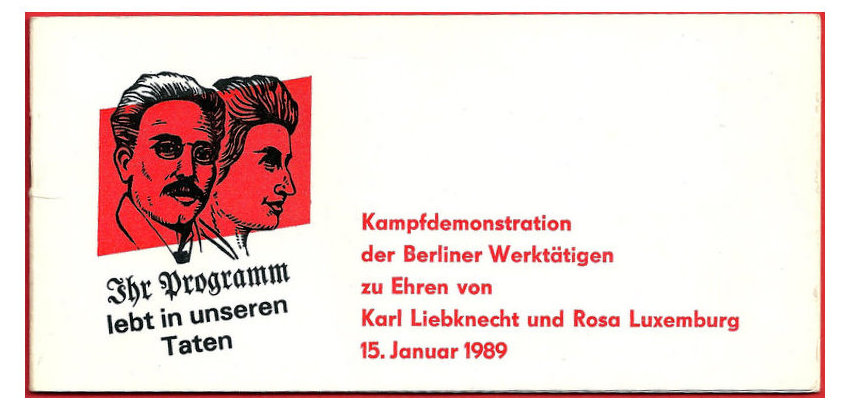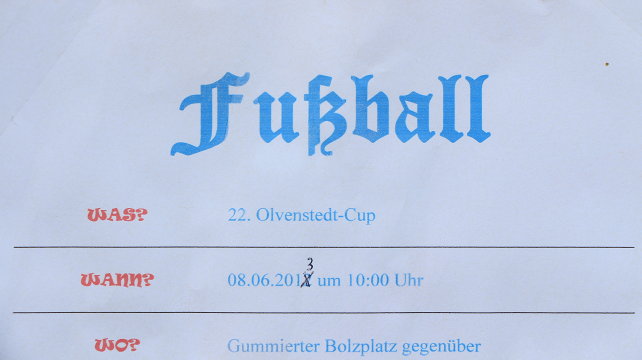
image-628738-galleryV9-lkcf.jpg Eine der spätesten staatsoffiziellen Verwendungen von Fraktur überhaupt? Interessant erscheint mir besonders, dass die Fraktur hier in einem aus offizieller DDR-Sicht positiven und zukunftsgerichteten Kontext verwendet wird, statt z.B. für angeblich überkommene bürgerlich-kapitalistische Ideen zu stehen.
Soweit ich mich an die wenigen Frakturanwendungen in der DDR erinnere, wurde diese eher im Sinne von »historisch; alt; abgeschlossene Periode« verwendet als im Sinne von »reaktionär; bürgerlich; faschistisch« — also alles in allem recht emotions- und ideologiefrei. Ich kann mich freilich auch nicht an moderne Adaptionen erinnern, die der Fraktur eine Brücke in die Gegenwartstypographie gebaut hätten. Fraktur war Geschichte — Punkt. Hatte Typoart eigentlich eine Fraktur im Angebot? Ich kann mich nicht erinnern. Sie war aus dem Alltag schon weitgehend verschwunden, aber, wie mir scheint, eher aus Desinteresse und allgemeiner Fortschrittsgläubigkeit heraus. Die offizielle Ästhetik war halt die eines Plattenbaus, das hat sich auch in der Typographie bemerkbar gemacht und da war für Schnörkel kein Platz.
Aber, wie gesagt: Seltsamerweise scheint der Fraktur ausgerechnet in der DDR die Discreditierung als Nazischrift erspart geblieben zu sein.
Hatte Typoart eigentlich eine Fraktur im Angebot?
Typoart hatte an gebrochenen Schriften die Luthersche Fraktur, die Caslon-Gotisch und eine Schwabacher im Sortiment. Als digitalisierte Version sind diese Schriften aus der Typoart-Bibliothek bei Elsner + Flake zu beziehen. (Die Verlinkungen führen dort hin.)
Luthersche Fraktur:
»Volker Küster wählte typische Merkmale aus und vereinigte sie mit viel Stilgefühl zu einer sehr geschlossen wirkenden Werkschrift. Noch schmaler, etwas kräftiger und vor allem mit reicheren Schmuckdetails versehen, präsentieren sich die Großkegelgrade, die der Grafiker Herbert Lemme zeichnete.«
Luthersche-Fraktur.jpg
Caslon-Gotisch:
»Die Fotosatz-Replik wurde von Erhard Kaiser künstlerisch betreut.«
Caslon-Gotisch.jpg
Schwabacher:
»Die künstlerische Überarbeitung durch Herbert Lemme orientierte sich an historischen Drucken. Anstelle der falschen Versalziffern, wie sie von anderen Schwabachertypen bekannt sind, wurden bei der vorliegenden Fotosatzschrift Minuskelziffern eingesetzt.«
Schwabacher.jpg
Kein Widerspruch, verehrter Pachulke. Ich meinte das mit den negativ bürgerlichen Konnotationen nur als Beispiel für etwas, das man vielleicht etwa erwarten können nicht dass es so war. Ich bin mir sicher, dass man zum Lutherjahr 1983 einiges an gebrochenen Schriften gesehen hat. Trotzdem hat mich die Verwendung hier für Liebknechts und Luxemburgs »Programm« einigermaßen überrascht. Denn dieses war nach offizieller Lesart ja alles andere als »historisch; alt; [Teil einer] abgeschlossene[n] Periode«.
Ich meinte das mit den negativ bürgerlichen Konnotationen nur als Beispiel für etwas, das man vielleicht etwa erwarten können – nicht dass es so war.
So in etwa hatte ich Dich auch verstanden.
Die Kombination von Fraktur und Grotesk im Beispiel war einfach das Mittel des Graphikers, die Verbindung der objektiv ja doch historischen Personen Liebknecht / Luxemburg mit der DDR-Gegenwart herzustellen. Und damit war er durchaus »auf Linie«.
Stimmt, so erklärt ist das durchaus plausibel. Ich wäre mir nur nicht sicher gewesen, ob die Bonze, die diese Arbeit abnehmen musste, das auch so logisch gesehen hätte und den armen Gestalter nicht etwa in Generalverdacht genommen hätte, L und L in eine »revanchistische« Ecke zu stellen. Du weißt ja selbst, mit welch Lächerlichkeiten man so anecken konnte.
Ich betrachte dieses Thema übrigens nicht als abgeschlossen. Wenn ihr noch andere Beispiele von Fraktur in der DDR herum zu liegen habt, immer her damit! :huhu:
Ich denke, durch die gut belegte Tradition von Fraktur in der KPD (Thälmann-Wahlplakate u. dgl.) wäre der Graphiker gut abgesichert gewesen. Vermutlich sind das auch die Assoziationen gewesen, die hier sowohl bei Graphiker als auch bei Zensurbehörde die entscheidenden Trigger betätigt haben.
Volker Küster wählte typische Merkmale aus und vereinigte sie mit viel Stilgefühl zu einer sehr geschlossen wirkenden Werkschrift.
Und das ist nicht nur Werbeunsinn sondern stimmt ausnahmsweise mal. Die Luthersche Fraktur ist eine der ausgeglichensten, schönsten Frakturschriften überhaupt. Und die Typoart-Luthersche dürfte die beste digital verfügbare Fraktur sein!
ich finde, bei einer fraktur sollten auch die ziffern gebrochen sein, zumindest so anmuten. und natürlich minuskelziffern sein *find*
Merkwürdigerweise sehen die Ziffern in gebrochen Schriften sehr oft wie Fremdkörper aus, die man noch schnell aus einer Antiqua eingefügt hat.
Ich finde auch, daß es am besten ist, wenn die Ziffern ordentlich gebrochen sind. Aber eine ausgeglichene, harmonische, sauber gezeichnete und gut ausgebaute Fraktur mit runden Ziffern ist mir lieber als eine schlechtere Schrift mit gebrochenen Ziffern.
Ich habe folgende Vermutung, wie es zu den runden Ziffern gekommen sein könnte:
Früher (19. Jh.) war es üblich, daß man in einer Setzerei nur Ziffern aus einer einzigen Schrift hatte, d. h. in allen Sätzkästen lagen die gleichen Ziffern. So konnte man, wenn man mal mehr Ziffern benötigte und ein Fach leer wurde, einfach die Ziffern aus einem anderen Kasten verwenden. Es könnte sein, daß man sich so daran gewöhnt hat, Fraktur mit runden Ziffern zu mischen.
Bei den digitalisierten Schriften ist natürlich gut möglich, daß man einen Druck als Vorlage verwendet hat, in dem auf diese Weise Frakturbuchstaben mit Antiquaziffern gemischt worden sind, die Ziffern also ursprünglich gar nicht zur Fraktur gehört haben.
• 9 Monate später...
Gebrochene Schriften sind in der DDR reichlich verwendet worden und hatten keinen ideologischen Geschmack. Sie wurden in der Buch- und Plakatkunst und für Akzidenzen angewendet, und Lehrlinge wurden im Bleisatz mit ihr vertraut gemacht. Verbreitet war die Sinkwitz-Gotisch von Paul Sinkwitz aus dem Jahre 1941, die oft für Urkunden verwendet wurde. Ich habe sie als Lehrling in Ostberlin Anfang der 1980er Jahre benutzt, später als angestellter Akzidenzer, und sie steht heute in meiner Werkstatt, kommt allerdings nur sehr selten zum Einsatz (im Gegensatz zur Unger-Fraktur). Bernhard Schnelles Darstellung (Link im vorigen Beitrag) kann ich bestätigen. Die ideologischen Zuschreibungen in Westdeutschland waren uns nicht geläufig, wir unterschieden zwischen schöner und häßlicher Schrift, nicht zwischen guter und böser.
Danke für die eindeutige Bestätigung meiner Aussage. Wenn ich früher den Design-Studenten diesen Sachverhalt zu erklären versucht habe,
wurde ich teilweise angeschaut, als ob ich von einem anderen Stern käme.
Vor ein paar Tagen gesehen: Fraktur in der, nun ja, »heutigen DDR«. :party:
olvenstedt-fussball-poster-2013.501295_s
(größeres Bild per Klick)
„Euch“ kann man es aber auch nicht recht machen! Da versucht der Fußballtournierankündigungszettelverantwortliche schon zu gestalten, ohne nur Arial oder TNR (oder eine der Schriften, „die genauso aussehen“) zu nehmen, greift dabei sogar um die Comic Sans herum – und dann ist es doch wieder falsch! :bandit:
Hoffentlich freuen sich wenigstens die Befürworter eines Fraktureinsatzes in allen modernen Lebenslagen. Immerhin geht es bei der Fußballtournierankündigung gar nicht um Geschichte.
…  ohne Arial oder TNR …
Also ich sehe da eine Times. Und sie ist nicht einmal das schlechteste auf diesem Zettel. Und gegen diese roten Dinger da links von der Times wäre selbst CS eine Wohltat.